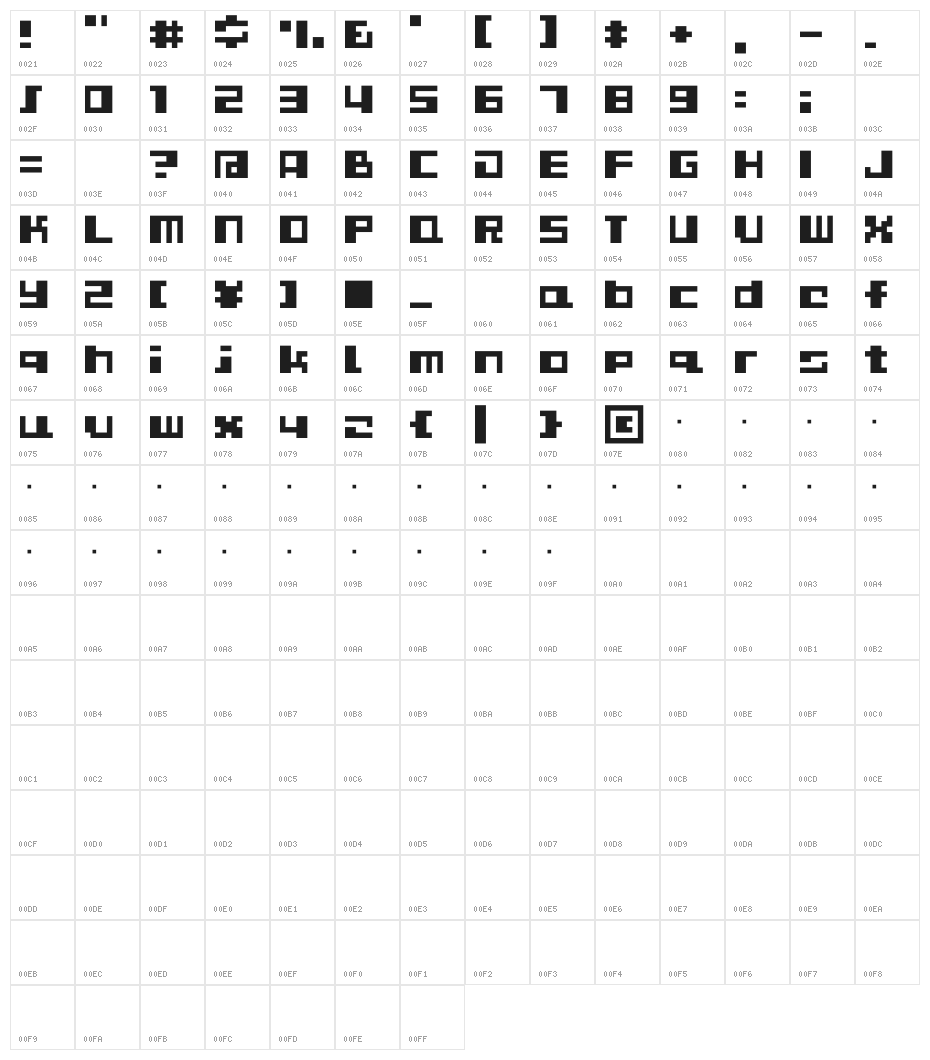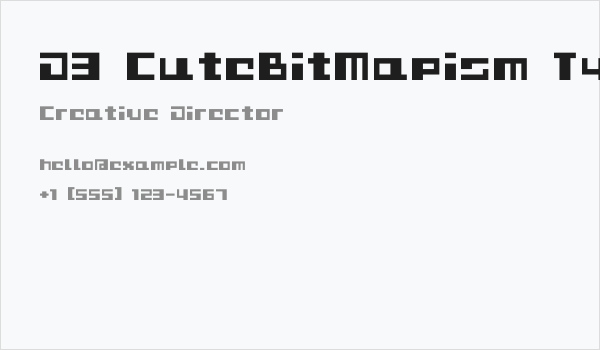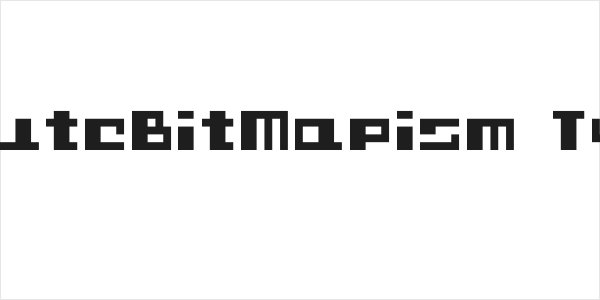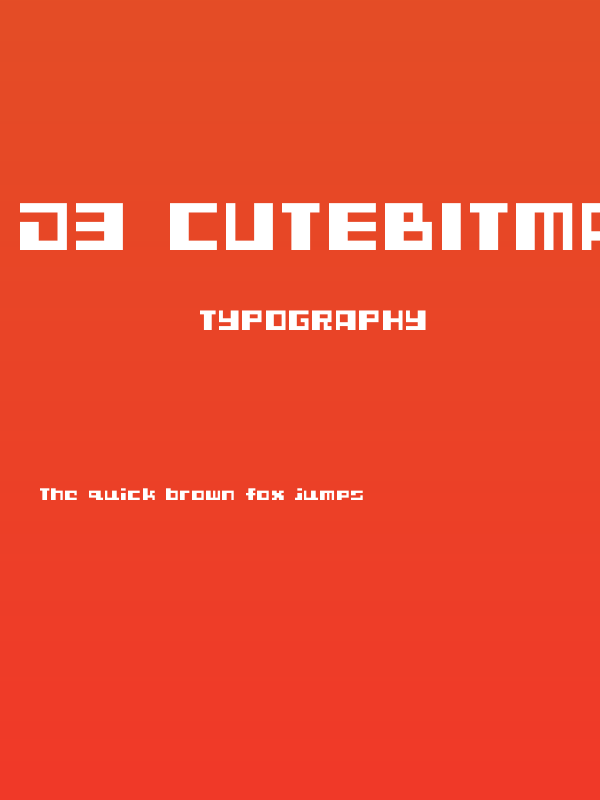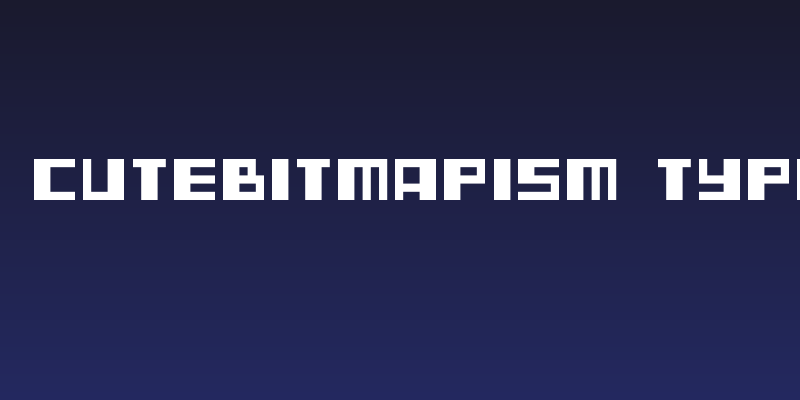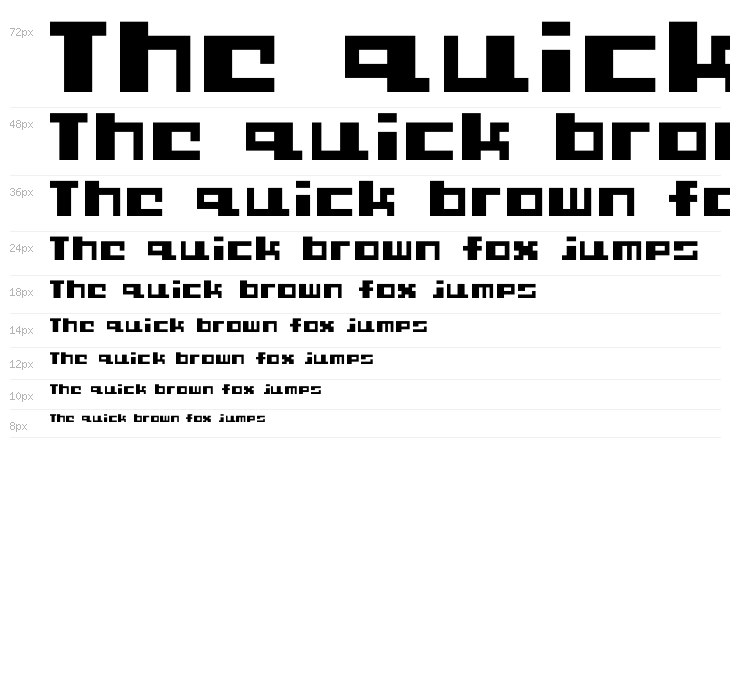
D3 CuteBitMapism TypeB Font
| Gesamtstil | Retro, Digital |
| Anwendungsfall | Headlines, Logos, Digital Art |
| Vorgeschlagene Projekte | Ideal for video game design, retro-themed posters, digital art projects, and tech-related branding. |